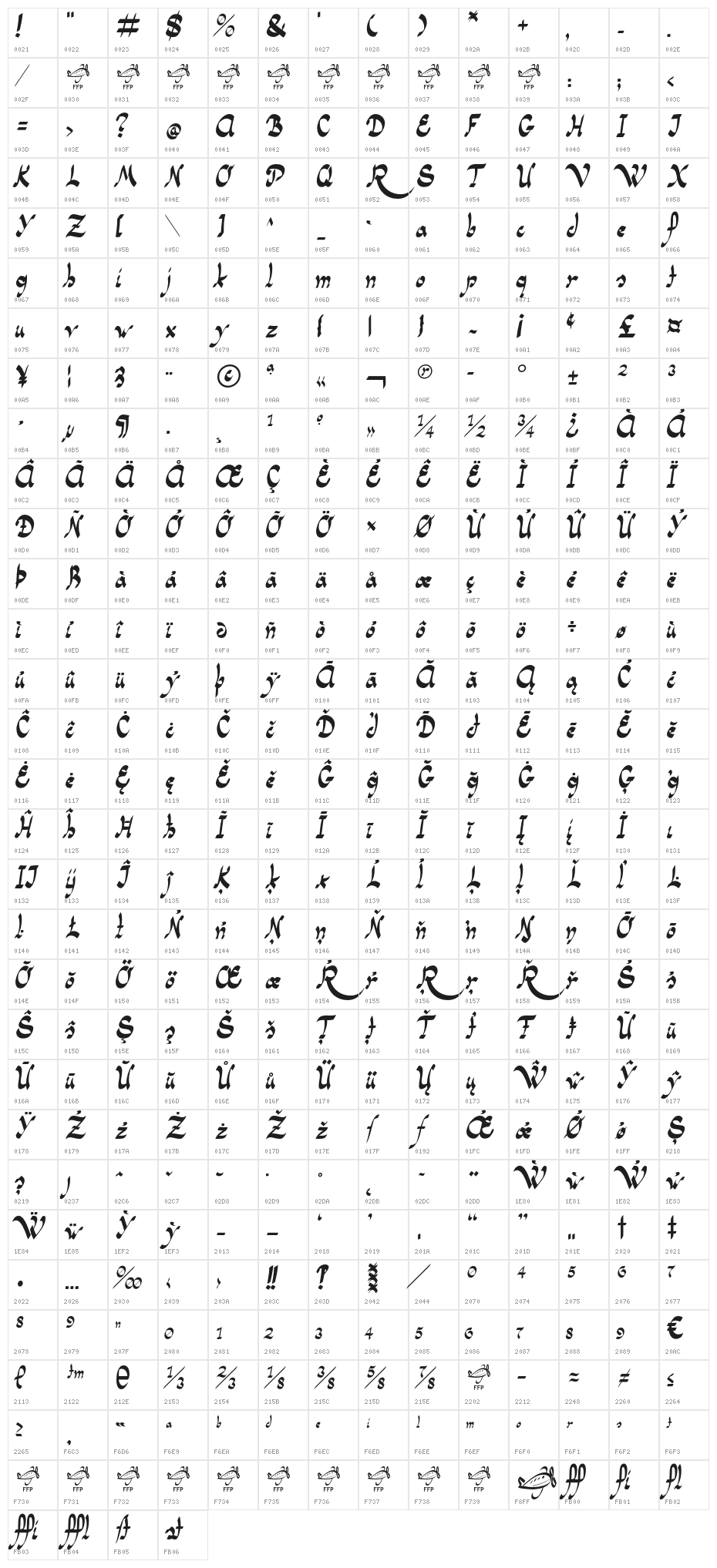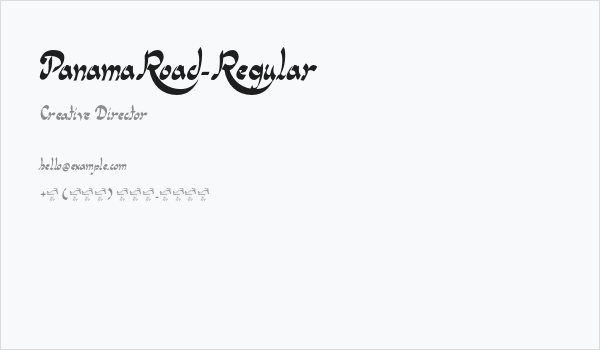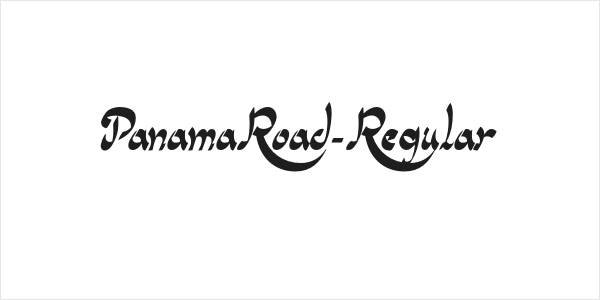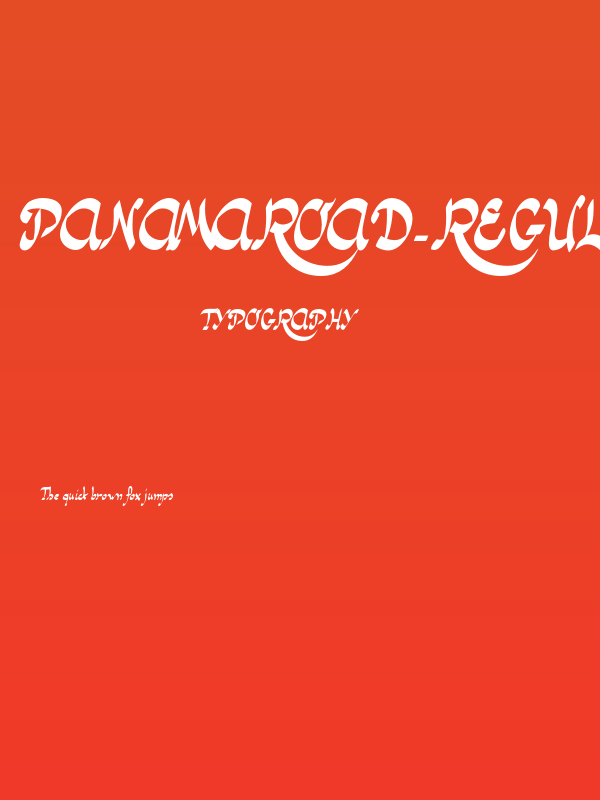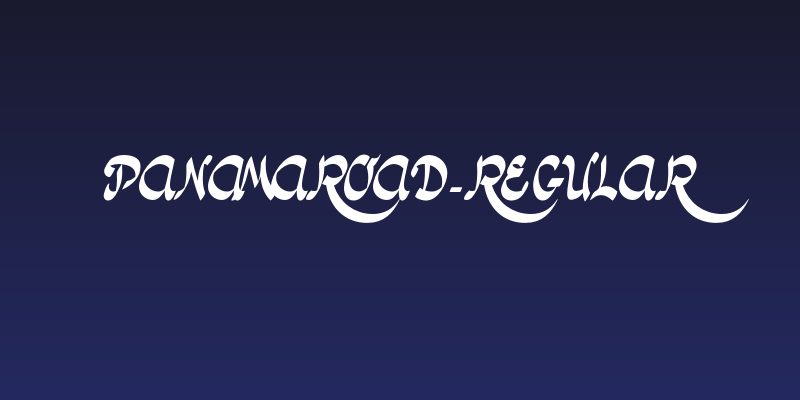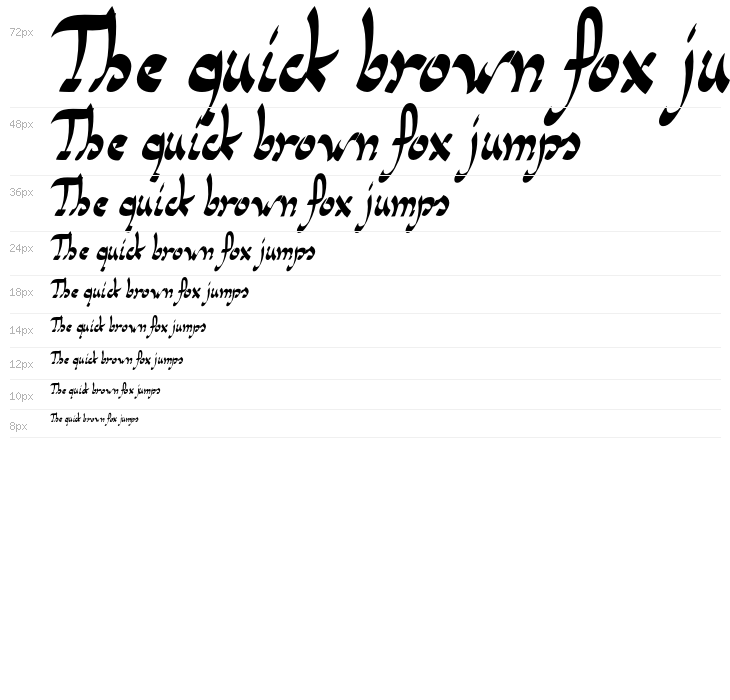
PanamaRoad-Regular Font
✎ Calligraphic
| Progetti proposti | Ideal for posters, branding, album covers, and any project requiring a bold, artistic touch. |